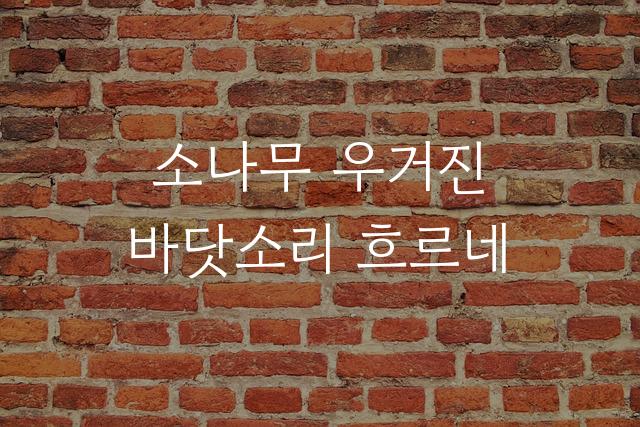
동글은 류양희가 제작한 부드러우면서도 친근감을 느낄 수 있는 한국어 폰트입니다. 동그란 형태가 특징인 이 폰트는 따뜻한 느낌을 전달하며, 읽기 쉬운 특성을 갖고 있습니다.
어린이 책, 인사말 카드, 소셜 미디어 등에서 자주 활용되며, 효과적인 메시지 전달에 적합합니다.
이 폰트는 교육, 라이프스타일, 유아/가족 분야에 잘 어울리며,
친근한, 귀여운, 편안한 느낌을 담고 있는 것이 특징입니다.